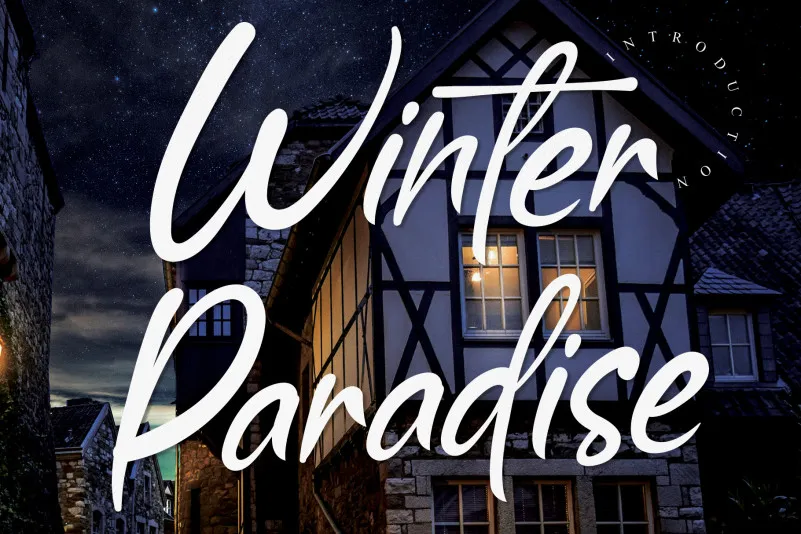
A fonte Winter Paradise Script é uma criação cuidadosamente pensada para quem aprecia o charme das impressões manuscritas. Idealmente adaptada para diversas situações, essa fonte traz um toque leve e descontraído que se assemelha a uma conversa informal entre amigos. Com seu ar um pouco engraçado e quirk, a Winter Paradise Script destaca-se como uma escolha perfeita para criar texturas elegantes em cartões de convite, anúncios de moda ou até mesmo em rascunhos poéticos. Seja ela usada em projetos digitais ou impressos, essa fonte manuscrita oferece um toque personalizado e encantador que certamente irá destacar seu trabalho. Ela é perfeita para designers buscando um estilo autêntico e despojado para suas criações. A Winter Paradise Script atinge o equilíbrio entre simplicidade e sofisticação, oferecendo aos criadores uma ferramenta versátil que não apenas impressionará seus leitores com seu aspecto encantador, mas também permitirá a eles expressar sua personalidade de maneira única.